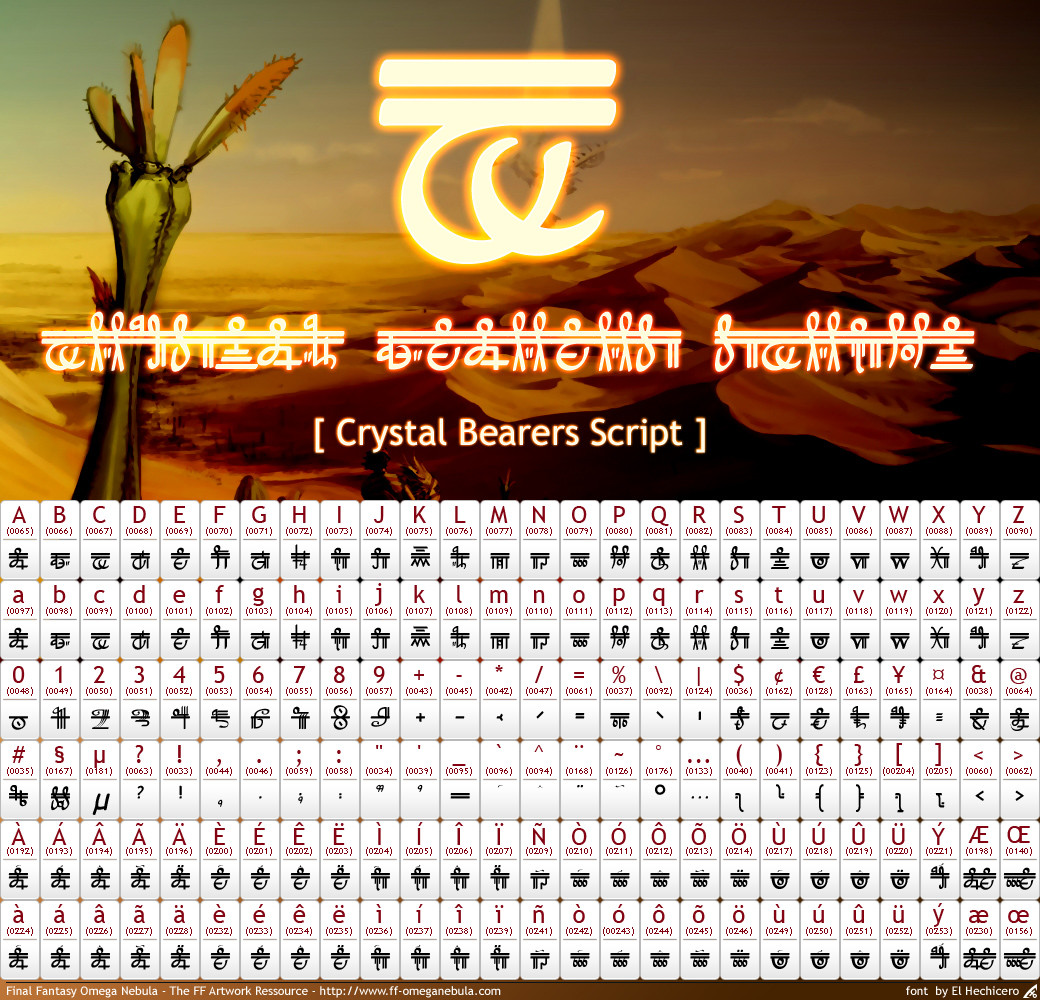
Police d'écriture utilisée dans Final Fantasy Crystal Chronicles : Crystal Bearers---------
Font used in Final Fantasy Crystal Chronicles : Crystal Bearers